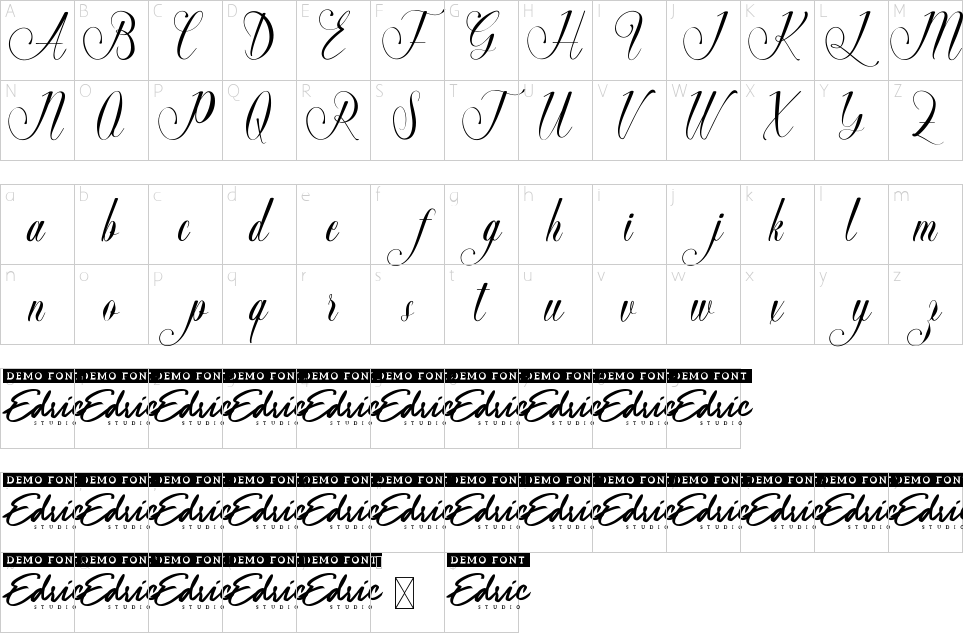
Descubra Anna Audrey, uma fonte moderna e elegante projetada para proporcionar um toque sofisticado a qualquer projeto. Esta fonte, cuidadosamente criada pela EdricStudio, é uma adição inovadora para o seu design. Com seus traços fluidos e sua disposição perfeita, Anna Audrey cria textos vibrantes e envolventes. Este design inovador tem sido baixado mais de 9.348 vezes, uma prova de sua popularidade e qualidade. Seja para aplicativos de web, design gráfico ou impressão, Anna Audrey é uma escolha inteligente para qualquer projeto. Baixe-a agora e dê um toque moderno e sofisticado a sua próxima criação.